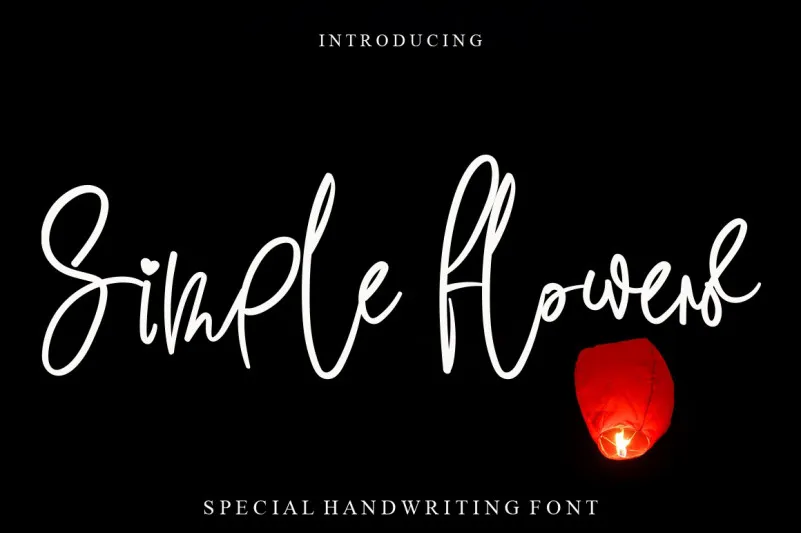
A Simple Flowers Font é uma elegante opção para quem busca uma mão-dura escrita que se assemelha a um desenho artesanal e delicado, sem qualquer compromisso com formas técnicas ou uniformidade. Especificamente criada por LevinCreative, essa fonte hand-writed foi projetada originalmente para uso pessoal, garantindo liberdade de criação sem restrições comerciais. Ao usar a Simple Flowers Font, você pode adicionar um toque suave e autêntico a seus documentos, presentes ou designs pessoais. Seu caráter fluido evoca sentimentos de serenidade e elegância, oferecendo uma maneira criativa para expressar sua individualidade através do texto. Ideal tanto para gráficos digitais quanto para obras manuscritas, essa fonte é perfeita para quem valoriza o handmade em seus projetos. Com a Simple Flowers Font, você pode transformar qualquer página de trabalho ou design em algo especial e pessoalmente único.